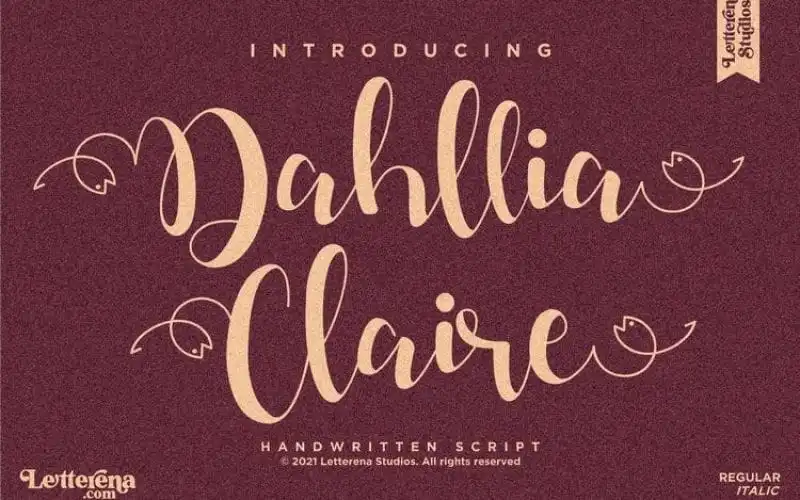
Dahllia Claire Calligraphy Font – Download Grátis
A Dahllia Claire é uma elegante fonte calligrafia criada pela Letterena Studios. Com seu traçado relaxado e fluiêncio, ela se destaca como a escolha perfeita para designers buscando dar um toque romântico em seus projetos. Esta fonte de script é extremamente versátil e enriquece designs variados, elevando-os ao nível mais alto. Ideal tanto para criações gráficas quanto para design de produtos, como logos, marcas, embalagens de produto, mugs e cartões promocionais, a Dahllia Claire oferece uma aposta segura para aqueles buscando um touch elegante e romântico em suas produções. Seja para projetos que exigem uma pitada de personalidade, como nome card, convites, cartas de cumprimento ou até mesmo camisetas de festa, essa fonte será uma escolha incrível. Não hesite em incorporá-la aos seus projetos e deixe seu trabalho brilhar com um toque único e charmoso.